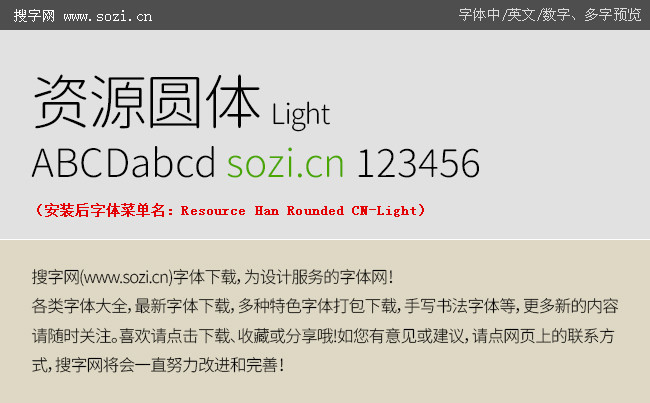
資源圓體Light
搜字網(wǎng)給大家提供一款資源圓體Light中文字體下載,資源圓體是一款基于思源黑體改造而成的免費(fèi)可商用圓體字體。除了資源圓體還有源柔黑體(也稱思源柔黑,由日本設(shè)計(jì)師改造,對(duì)日文支持較好)和源泉圓體(由臺(tái)灣設(shè)計(jì)師改造,對(duì)繁體支持較好)也都是基于思源黑體改造而成的免費(fèi)圓體字體。相對(duì)于源柔黑體和源泉圓體,資源圓體則對(duì)簡(jiǎn)體字體支持較好,因?yàn)樗怯蓢?guó)內(nèi)設(shè)計(jì)師Cyano Hao基于中國(guó)版的思源黑體改造而成的圓體字體。